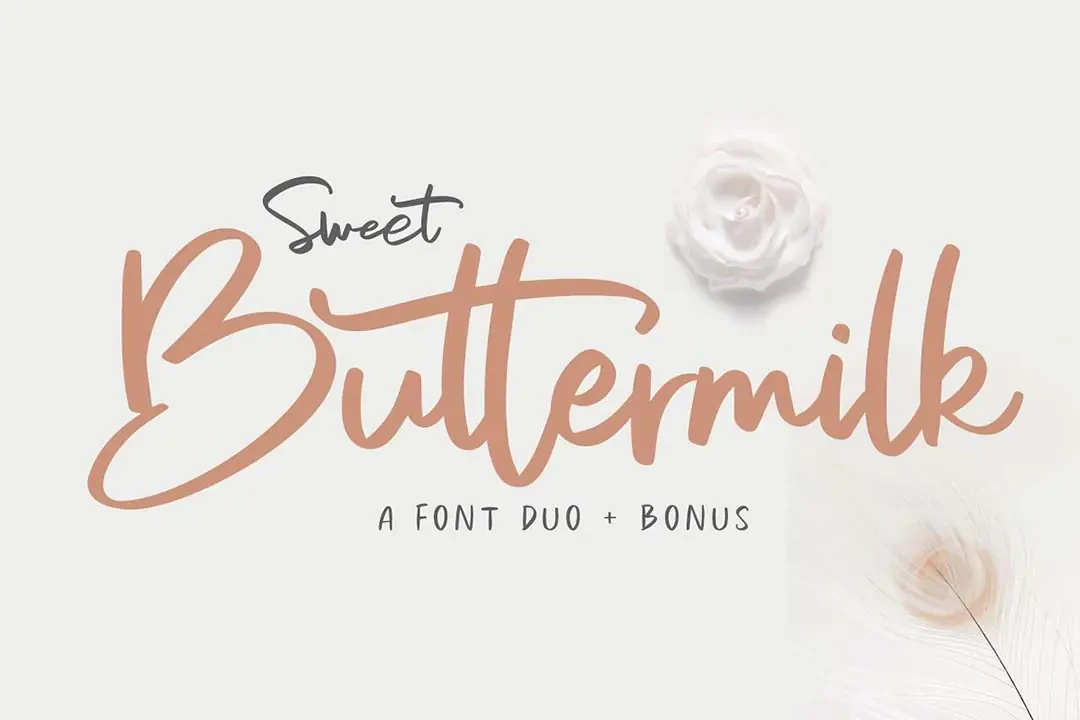
Sweet Buttermilk Handwritten Script Font
Sweet Buttermilk - Font Duo + Bonus, gerçek el yazısını ifade eden bir el yazısı fontudur ve tipinizi heyecan verici ve güzel bir çalışma parçasına dönüştürmenizi sağlar. Düzensiz, el yazısı görünümlü bu font, gerçek bir insan dokunuşu katar ve çok sayıda sevgiyle hazırlanmış ayrıntılarla birlikte
Sweet Buttermilk - Font Duo + Bonus gerçek el yazısının ifadesine dayanan bir el yazısı fontudur ve tipinizi heyecan verici ve güzel bir çalışma parçasına dönüştürmenizi sağlar. Düzensiz, el ile yazılmış görünüme sahip olan bu font, işlere gerçek bir insan dokunuşu katar ve birçok sevgiyle hazırlanmış ayrıntılarla birlikte gelir. Tüm yazı tipi stillerini istediğiniz gibi birleştirin, bazı süsleyici kıvrımlar veya afişler ekleyin ve tek bir kelime bile muhteşem hale gelir.